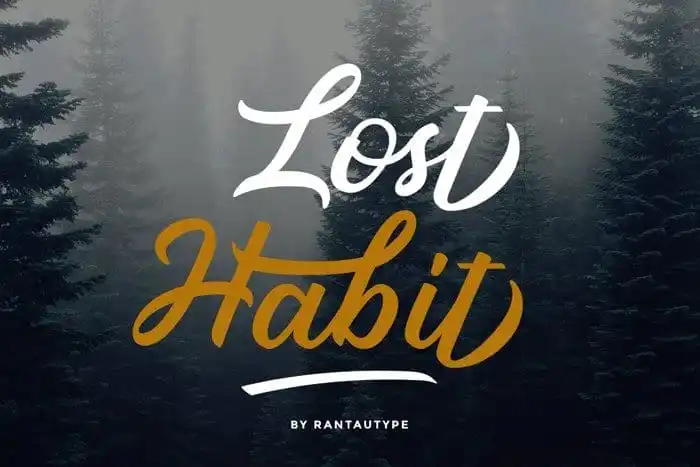
Lost Habit Calligraphy Font – Download Grátis
A Lost Habit Calligraphy Font é uma fonte script elegante, perfeitamente adaptada para criações que exaltam o estilo feminino. Seu charme suave e delicado se destaca entre outras fontes de scripts, e oferece caracteres alternativos minúsculos com um toque adicional de entalhe. Excelente para trabalhos em logotipos, identidade visual, campanhas promocionais, criação de citações, embalagens, desenho de camisetas, merchandise e até mesmo design de panfletos ou materiais para redes sociais. Perfeita para transformar seu trabalho ou negócio no topo da sua categoria. Lost Habit está aqui para fazer você brilhar!